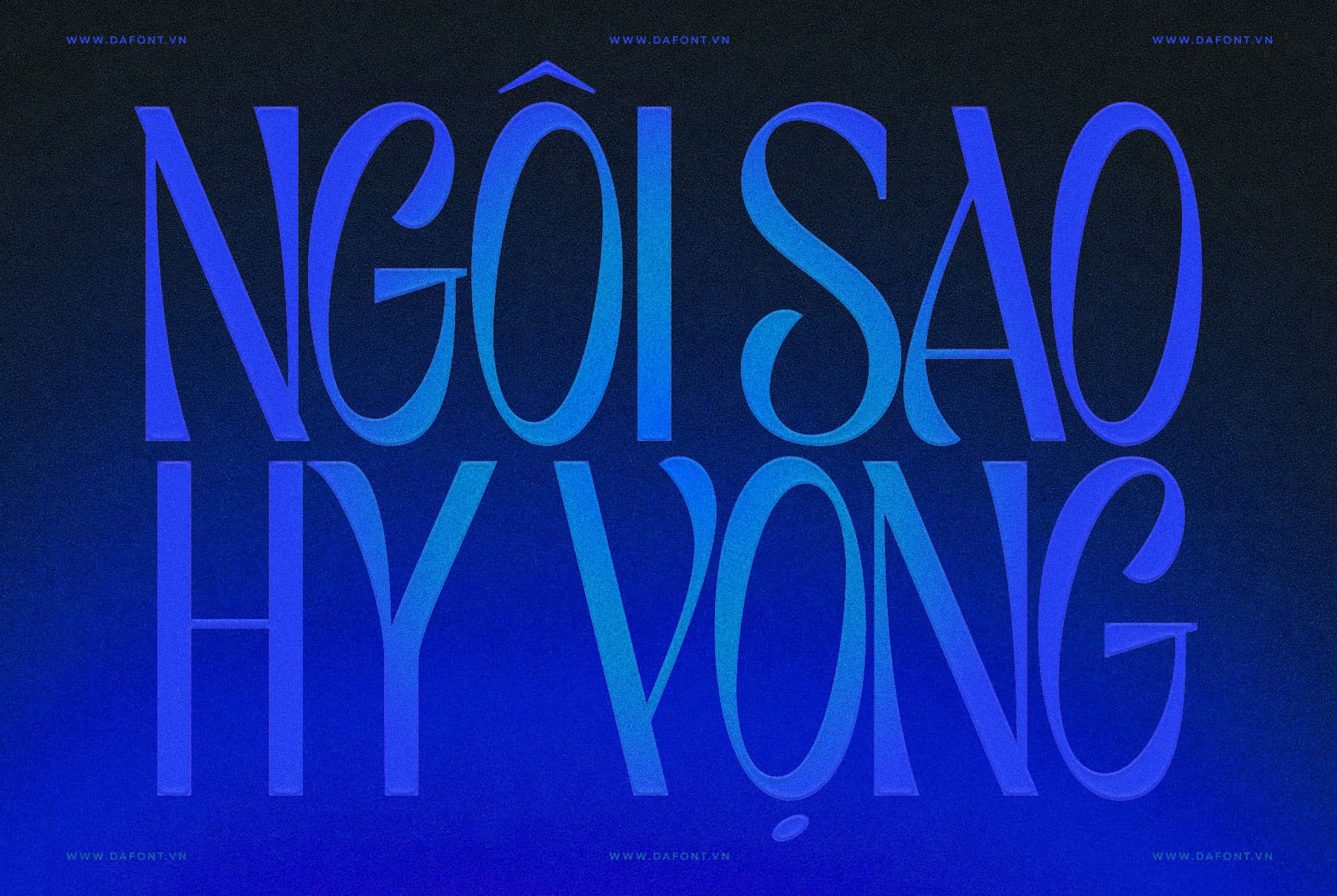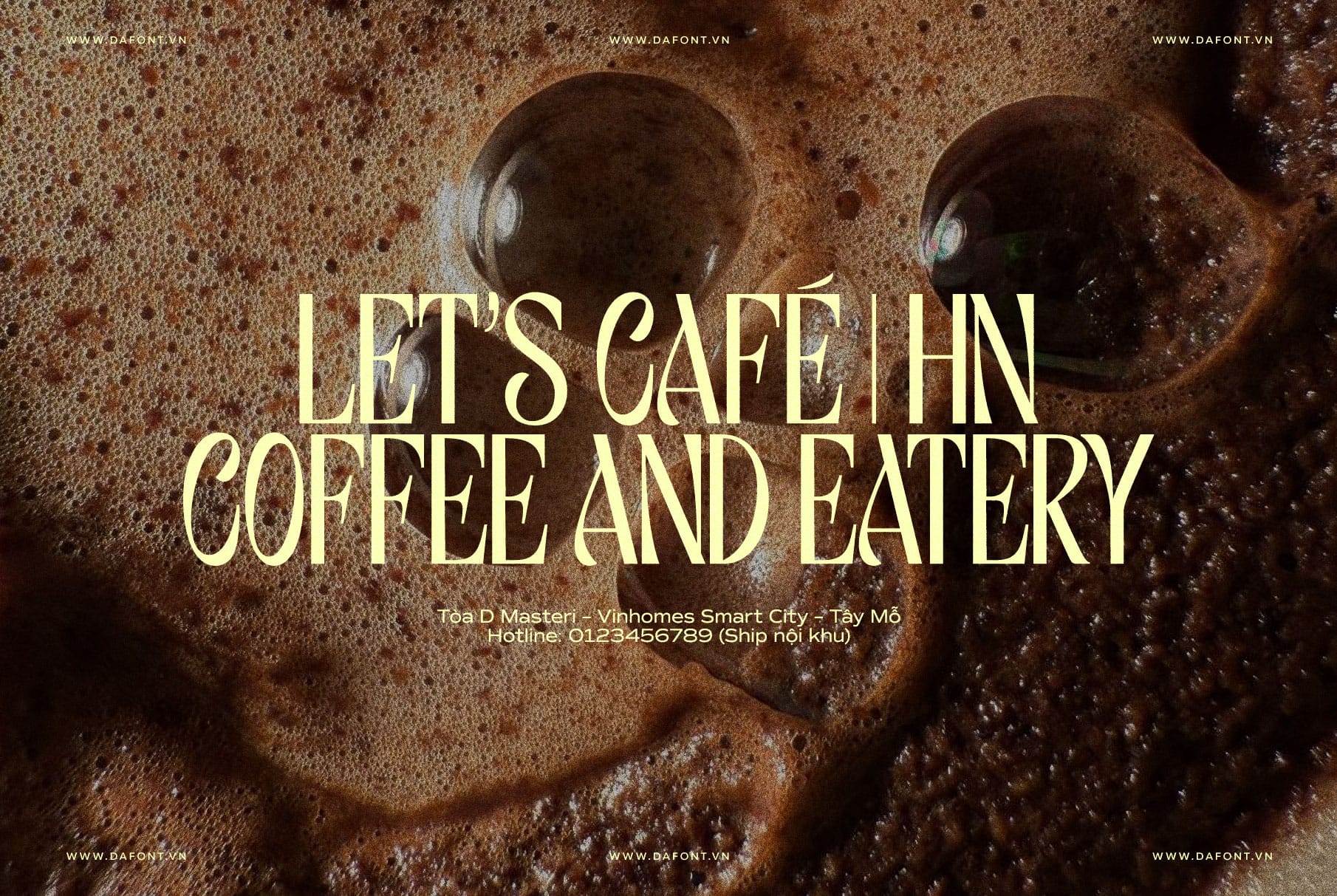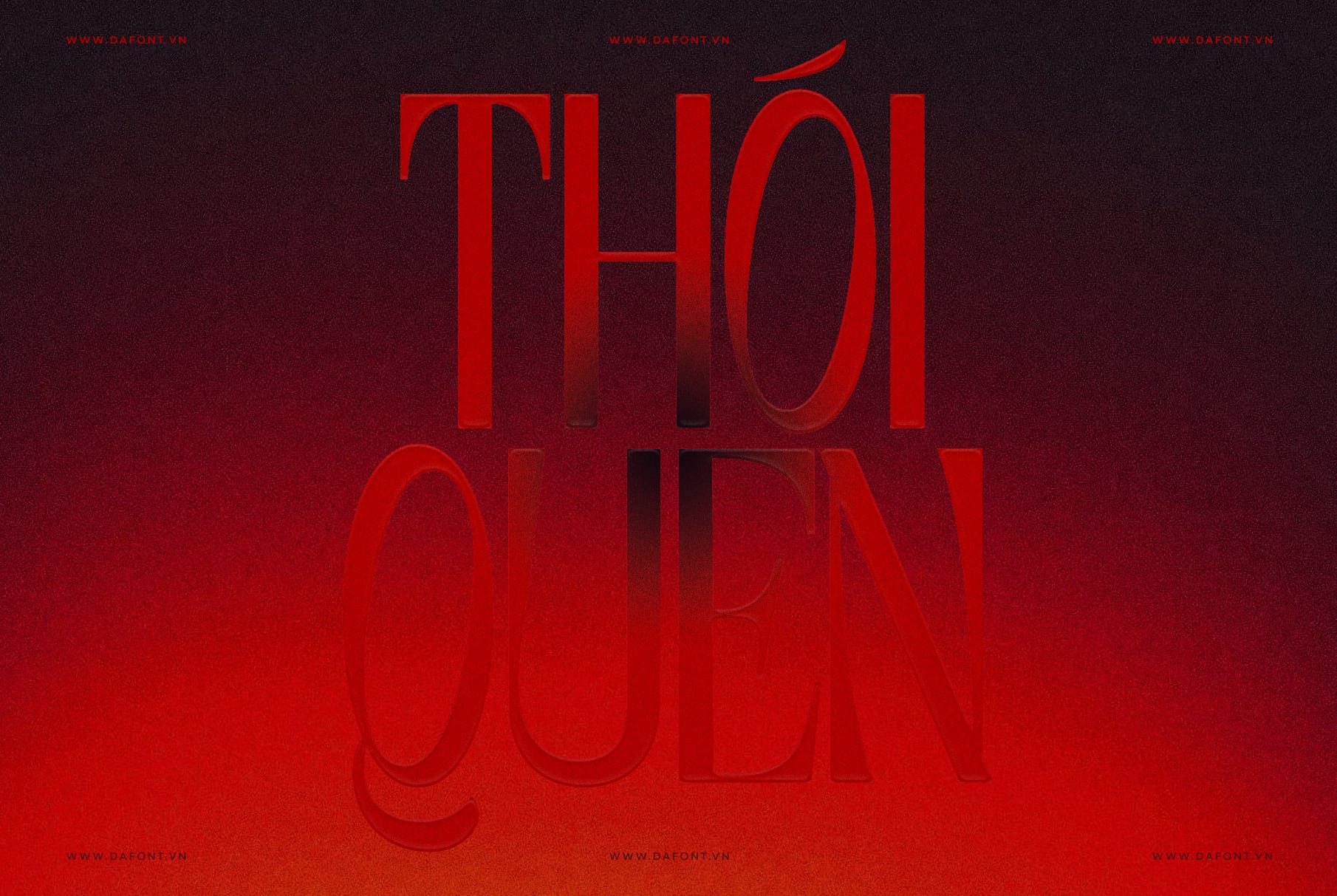
DFVN TAN – JARDINIERE
Font sans-serif lấy cảm hứng từ mid-century
DFVN TAN – JARDINIERE là một phông chữ sans-serif đang thu hút sự chú ý của các nhà thiết kế đồ họa và thương hiệu trên toàn thế giới. Lấy cảm hứng từ phong cách mid-century, font này kết hợp sự thanh lịch cổ điển với nét hiện đại, mang đến sự cân bằng hoàn hảo giữa vintage và contemporary. Nếu bạn đang tìm kiếm một phông chữ đa năng cho dự án branding, packaging hay nội dung mạng xã hội, TAN – JARDINIERE chắc chắn là lựa chọn đáng cân nhắc.
DFVN TAN – JARDINIERE hợp với dự án nào?
TAN – JARDINIERE là lựa chọn lý tưởng cho nhiều lĩnh vực thiết kế nhờ tính đa năng và sức hút thẩm mỹ. Dưới đây là các use case “ăn điểm” của JARDINIERE:
• Branding/Logo: hợp brand thời trang, mỹ phẩm, lifestyle, café/bar, boutique.
• Packaging: tạo cảm giác cao cấp, có chất cổ điển nhưng trẻ.
• Editorial/Poster: hợp bìa tạp chí, tiêu đề bài viết, ấn phẩm nghệ thuật.
• Social & Digital: tiêu đề, quote card, key visual cho campaign.
Mẹo nhanh: JARDINIERE thường “đẹp nhất” khi dùng cho headline hoặc display text; nếu dùng body text dài, hãy test kỹ độ đọc (size/leading/contrast) theo ngữ cảnh dự án.
Gợi ý kết hợp font đẹp với DFVN TAN – JARDINIERE
Để giữ đúng tinh thần “retro chic”, bạn có thể phối:
• JARDINIERE (headline) + một sans serif trung tính (body) để cân bằng cá tính.
• JARDINIERE + một serif editorial (phụ đề/quote) nếu bạn muốn cảm giác thời trang, tạp chí.
Kết hợp font tốt nhất vẫn là dựa trên brand voice và ngôn ngữ bạn dùng.
Kết luận
Nếu bạn đang tìm một font sans serif vừa tối giản vừa có cá tính, DFVN TAN – JARDINIERE là lựa chọn rất “đúng bài”. Đây là typeface theo tinh thần mid-century, mang vẻ thanh lịch nhưng vẫn có độ nghịch ngợm ở nét chữ và tỷ lệ, giúp thiết kế nhìn “đắt giá” hơn mà không hề lỗi thời.
Tóm lại, TAN – JARDINIERE là một lựa chọn đáng cân nhắc khi bạn cần một kiểu chữ vừa có gu, vừa retro hiện đại, dễ ứng dụng cho branding, poster, editorial hay nội dung số. Chỉ cần dùng đúng ngữ cảnh (đặc biệt ở headline/điểm nhấn). JARDINIERE có thể giúp thiết kế của bạn nổi bật, có chất và bền dáng theo thời gian.